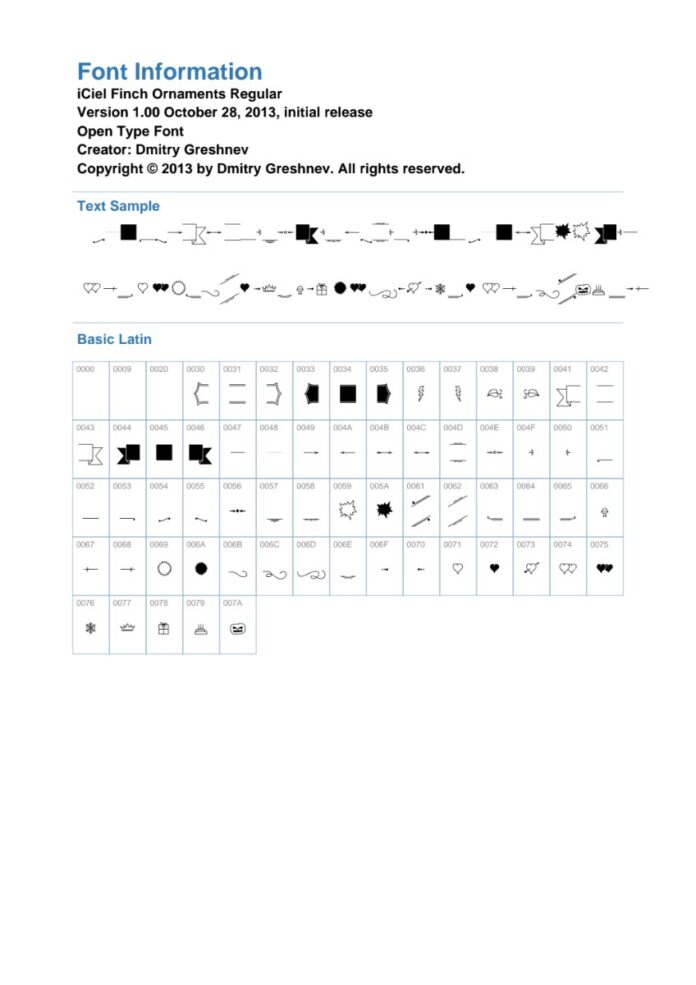
Font iCiel Finch Ornaments. Khám phá font iCiel Finch Ornaments độc đáo tại Poster.vn, một bộ font trang trí với các ký tự đặc biệt, hoàn hảo cho thiết kế thiệp, logo và các ấn phẩm sáng tạo, mang đến vẻ đẹp tinh tế và nghệ thuật.
Trong thế giới thiết kế đồ họa, việc lựa chọn font chữ phù hợp có thể tạo nên sự khác biệt lớn cho bất kỳ dự án nào. Và khi nói đến sự độc đáo, tinh tế và đầy tính nghệ thuật, font iCiel Finch Ornaments là một cái tên không thể bỏ qua. Tại Poster.vn, chúng tôi tự hào giới thiệu bộ font đặc biệt này, một công cụ mạnh mẽ giúp các nhà thiết kế thỏa sức sáng tạo và tạo ra những tác phẩm ấn tượng.
Giới thiệu về Font iCiel Finch Ornaments
iCiel Finch Ornaments không chỉ là một font chữ thông thường; nó là một bộ sưu tập các ký tự trang trí, biểu tượng và hình dạng độc đáo, được thiết kế để bổ sung và làm phong phú thêm cho các thiết kế của bạn. Được phát triển bởi Dmitry Greshnev và phát hành lần đầu vào tháng 10 năm 2013, bộ font này nhanh chóng trở thành lựa chọn yêu thích của nhiều nhà thiết kế nhờ vào sự đa dạng và tính ứng dụng cao.
Với iCiel Finch Ornaments, bạn không chỉ có các chữ cái và số mà còn có hàng trăm ký tự đặc biệt, từ các họa tiết hoa văn, đường viền, đến các biểu tượng nhỏ xinh, tất cả đều được thiết kế với sự tỉ mỉ và tinh xảo. Điều này mở ra vô vàn khả năng sáng tạo, cho phép bạn tạo ra những thiết kế độc đáo mà không cần phải tìm kiếm thêm các yếu tố đồ họa khác.
Đặc điểm nổi bật của Font iCiel Finch Ornaments
Font iCiel Finch Ornaments sở hữu nhiều đặc điểm nổi bật khiến nó trở thành một tài nguyên quý giá cho mọi nhà thiết kế:
- Đa dạng ký tự trang trí: Đây là điểm mạnh lớn nhất của font này. Thay vì chỉ cung cấp các ký tự chữ cái và số, iCiel Finch Ornaments tập trung vào các họa tiết, biểu tượng và đường viền trang trí. Điều này giúp bạn dễ dàng thêm các chi tiết nghệ thuật vào thiết kế của mình.
- Phong cách độc đáo: Các ký tự trong font mang phong cách cổ điển nhưng vẫn rất hiện đại, phù hợp với nhiều loại hình thiết kế khác nhau, từ thiệp mời, logo, bao bì sản phẩm đến các ấn phẩm truyền thông.
- Dễ dàng sử dụng: Mặc dù có nhiều ký tự đặc biệt, font này được thiết kế để dễ dàng truy cập và sử dụng trong hầu hết các phần mềm thiết kế đồ họa phổ biến như Adobe Illustrator, Photoshop, InDesign, v.v.
- Tính linh hoạt cao: Bạn có thể kết hợp các ký tự của iCiel Finch Ornaments với các font chữ khác để tạo ra sự tương phản và điểm nhấn, hoặc sử dụng chúng độc lập để tạo ra các họa tiết trang trí tinh xảo.
Ứng dụng của Font iCiel Finch Ornaments trong thiết kế
Với sự đa dạng và độc đáo của mình, font iCiel Finch Ornaments có thể được ứng dụng trong rất nhiều lĩnh vực thiết kế:
1. Thiết kế thiệp mời và thiệp chúc mừng:
Đây là một trong những ứng dụng phổ biến nhất của font này. Các họa tiết và đường viền trang trí giúp tạo ra những tấm thiệp mời cưới, thiệp sinh nhật, thiệp chúc mừng lễ hội trở nên sang trọng, tinh tế và cá nhân hóa hơn. Bạn có thể sử dụng các ký tự để tạo khung viền, phân chia các phần nội dung hoặc làm điểm nhấn cho tiêu đề.
2. Thiết kế logo và branding:
Đối với các thương hiệu muốn thể hiện sự tinh tế, cổ điển hoặc nghệ thuật, iCiel Finch Ornaments có thể là một lựa chọn tuyệt vời. Các biểu tượng và họa tiết có thể được tích hợp vào logo, tạo ra một dấu ấn độc đáo và dễ nhận diện. Nó đặc biệt phù hợp với các ngành như thời trang, trang sức, thủ công mỹ nghệ, nhà hàng cao cấp.
3. Thiết kế bao bì sản phẩm:
Để làm nổi bật sản phẩm và thu hút sự chú ý của khách hàng, bao bì đóng vai trò rất quan trọng. iCiel Finch Ornaments có thể giúp bạn tạo ra các họa tiết trang trí đẹp mắt trên bao bì, mang lại cảm giác sang trọng, độc đáo và chất lượng cao cho sản phẩm.
4. Thiết kế ấn phẩm in ấn và truyền thông:
Từ poster, brochure, tạp chí đến các ấn phẩm quảng cáo, font này có thể được sử dụng để thêm các yếu tố trang trí, làm cho bố cục trở nên sinh động và hấp dẫn hơn. Nó giúp phá vỡ sự đơn điệu của văn bản thuần túy và thêm một lớp nghệ thuật vào thiết kế.
5. Thiết kế web và UI/UX:
Mặc dù chủ yếu là font trang trí, các ký tự của iCiel Finch Ornaments vẫn có thể được sử dụng một cách khéo léo trong thiết kế web để tạo ra các icon, biểu tượng hoặc các yếu tố trang trí nhỏ, giúp giao diện người dùng trở nên độc đáo và thu hút hơn.
Hướng dẫn sử dụng Font iCiel Finch Ornaments hiệu quả
Để tận dụng tối đa sức mạnh của iCiel Finch Ornaments, bạn có thể tham khảo một số mẹo sau:
- Kết hợp hài hòa: Font này hoạt động tốt nhất khi được kết hợp với các font chữ đơn giản, dễ đọc. Hãy sử dụng iCiel Finch Ornaments cho các tiêu đề, điểm nhấn hoặc các yếu tố trang trí, và dùng font chữ cơ bản cho phần nội dung chính.
- Không lạm dụng: Vì là font trang trí, việc sử dụng quá nhiều ký tự từ iCiel Finch Ornaments có thể khiến thiết kế trở nên rối mắt. Hãy sử dụng một cách có chọn lọc và tinh tế để tạo điểm nhấn.
- Khám phá bảng ký tự: Hầu hết các phần mềm thiết kế đều có bảng ký tự (Glyphs panel) cho phép bạn xem và chọn tất cả các ký tự đặc biệt có trong font. Hãy dành thời gian khám phá để tìm ra những họa tiết phù hợp nhất với ý tưởng của bạn.